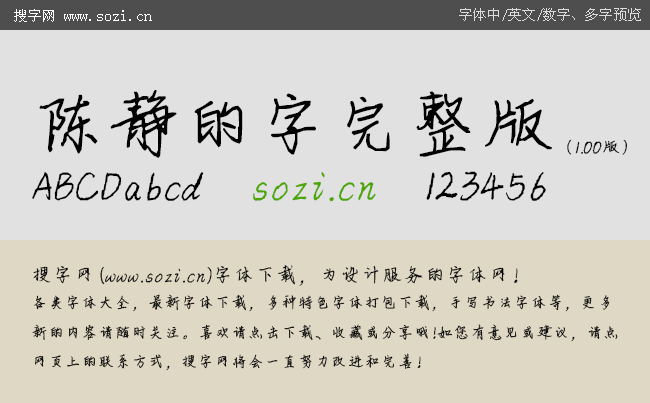
陳靜的字完整版
搜字網(wǎng)提供一款陳靜的字完整版中文書法字體下載陳靜的字完整版是一款手寫風(fēng)格的鋼筆書法字體,字體書寫流暢,字形大方,整體效果十分出色,適合應(yīng)用于廣告設(shè)計(jì)、名片設(shè)計(jì)、包裝印刷、產(chǎn)品設(shè)計(jì)等應(yīng)用。